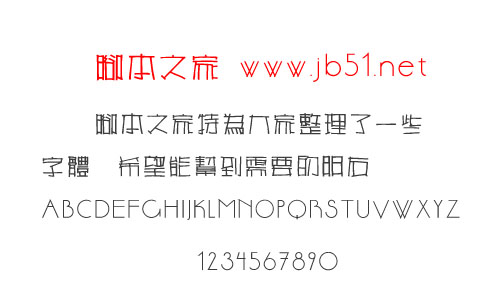
雅坊美工05字體是一款獨(dú)特的美術(shù)字體,該字體整體感覺非常纖細(xì),擁有上下比較拉長的效果,特別是帶有口的字,感覺中間的口都被拉長了,而且中文字體還具有手寫風(fēng)格特色,可以應(yīng)用于文本裝潢、信息展示、頁設(shè)計(jì)、篆刻制模、數(shù)據(jù)制作、裝潢設(shè)計(jì)、計(jì)算藝術(shù)設(shè)計(jì)、視覺設(shè)計(jì)、字帖等一切合法應(yīng)用場景,歡迎有需要的朋友前來下載使用。